书法作为我们国家传统文化的一部分,千年来一使人沉醉其中。书法人才层出不穷,有的另辟蹊径开创新流派,不过有的因为没法儿 识别字体,欣赏的人寥寥无几。有的艺术作品或许确是曲高和寡,但下面这些书法字体你一定能感受的它的美。
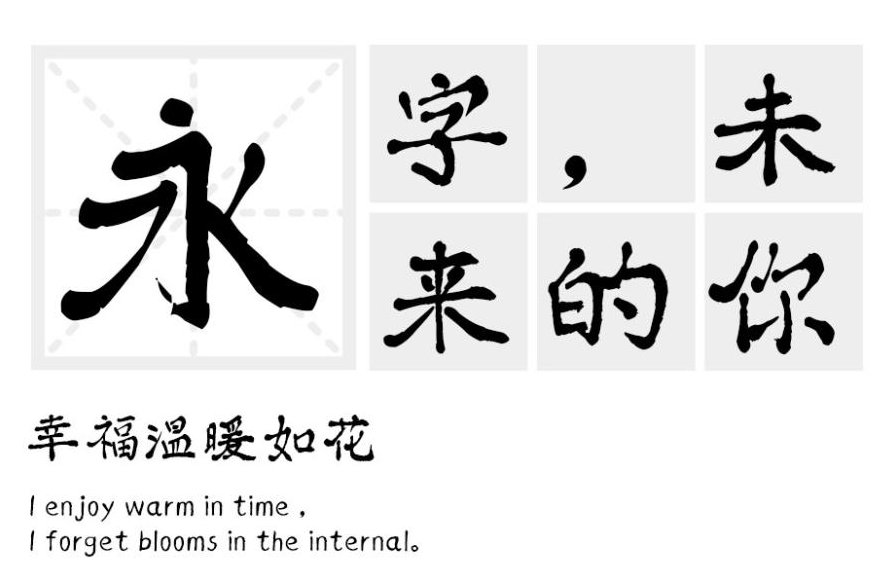
汉标熟宣毛笔体:这是一款带有书法味道的纯手写字体。将隶书与楷书笔画相结合,它的字形偏方一些。笔画中也减少了过多的处理和笔势,显得厚重,十分饱满。因为是纯手写,它更有独特的气质,看似统一,其实各领风骚。每个字都诠释出不同的风情。自由自在便是对它最好的诠释。
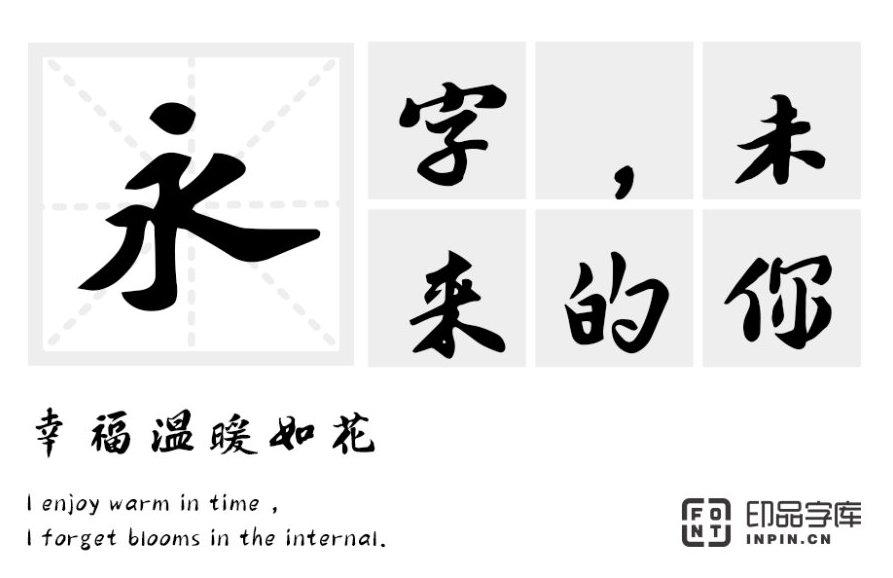
印品赤壁赋体: 这款字体灵感来源于北宋文学家苏轼创作的一篇试赋。全赋在布局与结构安排中映现了他独特的艺术构思,清韵深致、理意透辟。这款字体通过线条的勾勒转折,使得字体衔接自然、顺畅,字形端正有序不失独创性。 看图找字 的话一眼就可以辨认出是哪款字体。